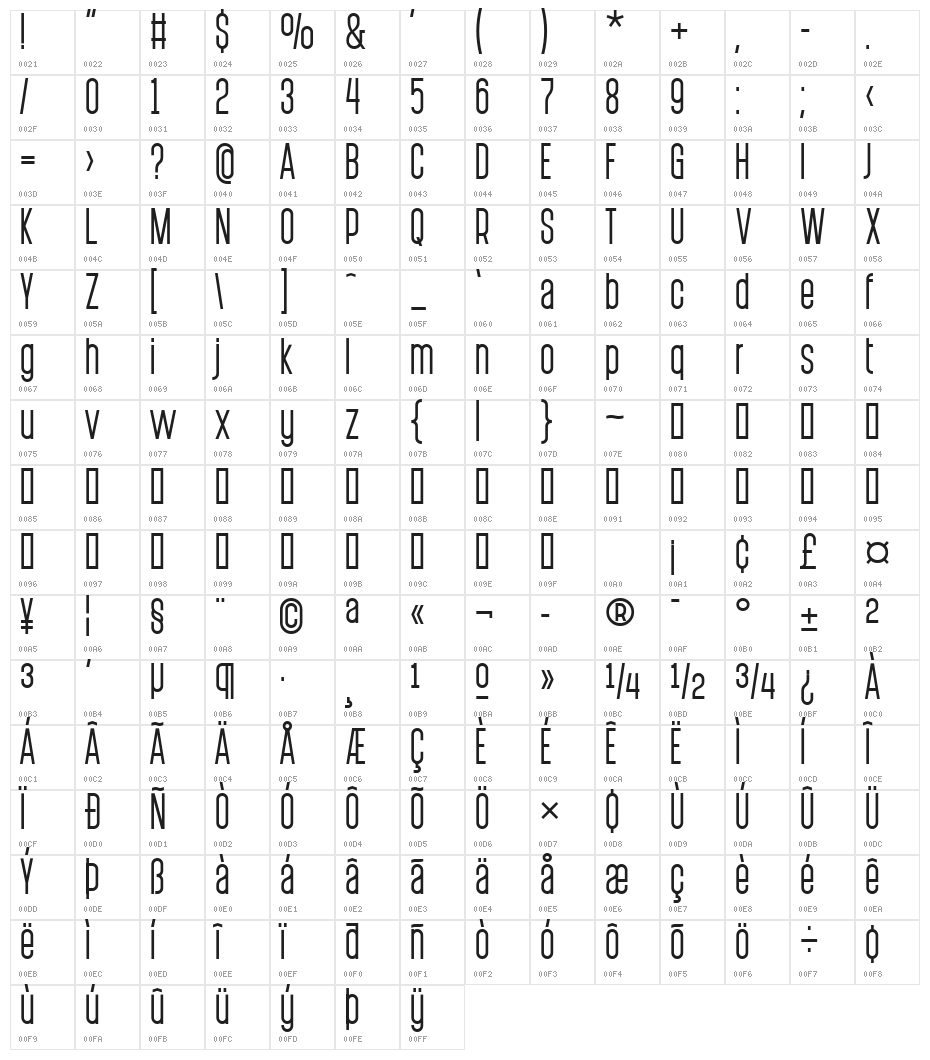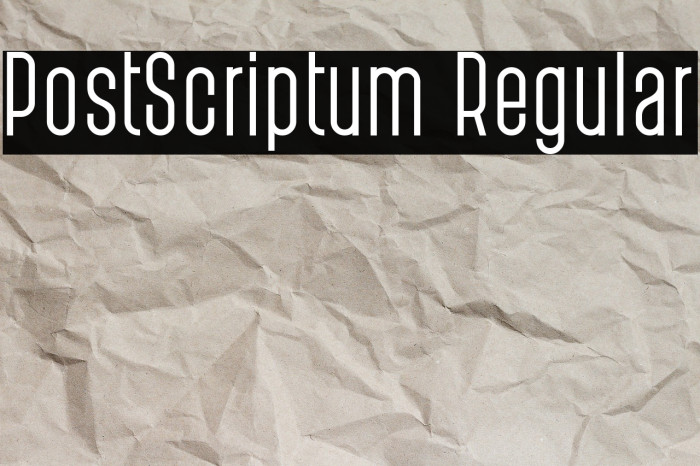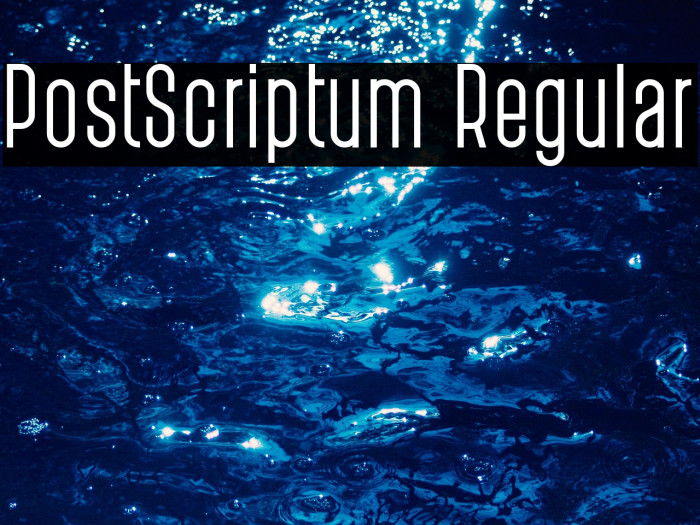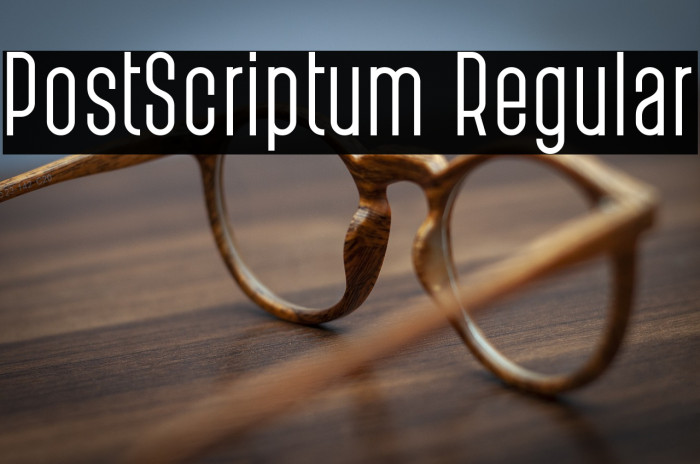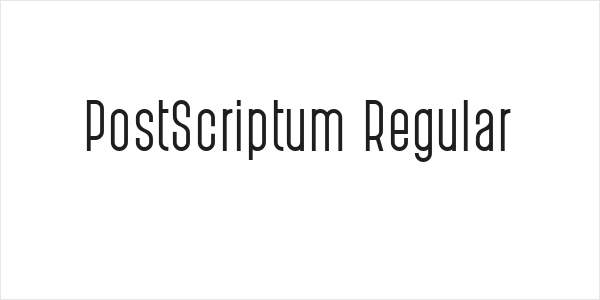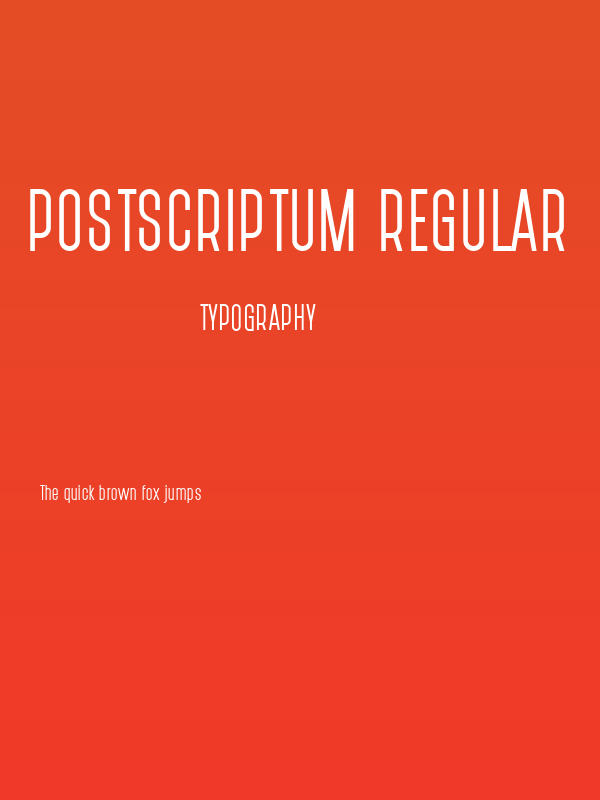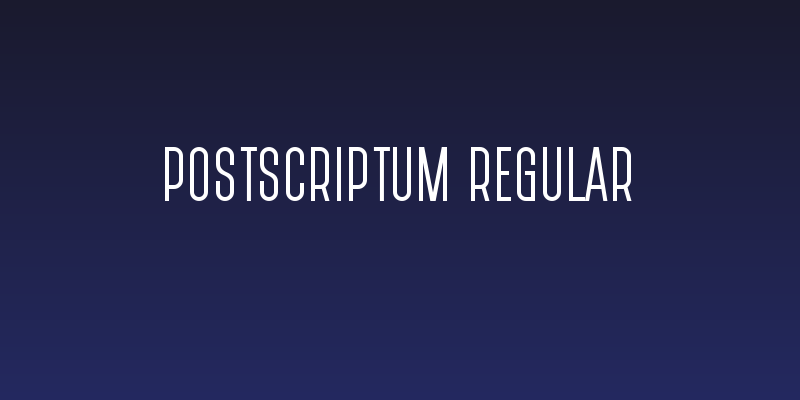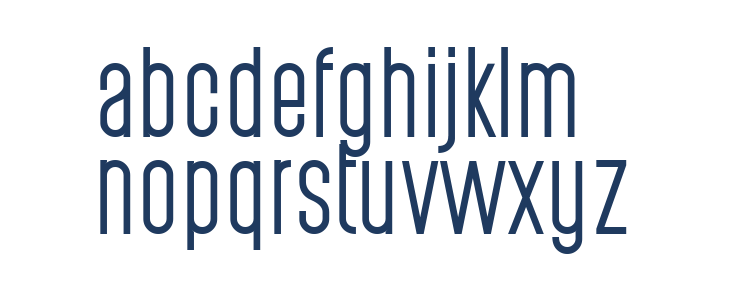
PostScriptum Regular Font
| 宽度 | Condensed |
| 使用场景 | Headlines, Body text, Logos |
| 推荐项目 | Ideal for branding, editorial design, web design, and advertising materials where a modern and clean look is desired. |